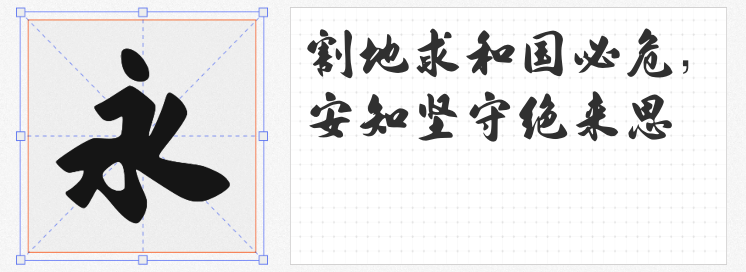
在文创设计的世界里,字体不仅是信息的载体,更是情感与文化的视觉表达。以下四款免费商用字体,以独特的风格与强适配性,为文创作品注入鲜活的个性,助力设计师轻松打造高辨识度作品。
1. 文心喜乐体
这款字体以“随性不拘谨”为设计核心,字形饱满圆润,笔画错落有致,横竖粗细对比强烈,形成视觉节奏感。高光纹理的加入赋予其手作质感,仿佛孩童涂鸦般充满天真趣味。无论是作为标题的吸睛焦点,还是正文的温馨陪伴,都能传递出轻松愉悦的氛围,尤其适合儿童文创、手账周边及生活类品牌设计。
2. 字库江湖古风体
以“古朴韵味”为基调,这款字体通过粗壮有力的笔画与柔和的视觉处理,平衡了历史厚重感与现代亲和力。它既保留了传统书法的骨力,又通过圆角处理减少锐利感,适用于餐饮品牌、传统工艺文创及国潮风格设计。无论是招牌、包装还是文化海报,都能以沉稳而不失温度的气质传递品牌底蕴。
3. 字体家AI造字霸行
由叶根友手写基础结合AI生成的这款字体,以“铿锵有力”的笔触展现力量美学。笔画刚劲挺拔,转折处利落分明,既保留了手写的自然韵律,又通过技术优化提升了排版适用性。适合需要强调品牌态度的文创场景,如潮玩包装、音乐节海报或运动品牌视觉,用硬朗风格传递个性主张。
4. 也字工厂小石头体
这款字体以“柔软可爱”为灵魂,字形如圆润石子般Q弹,笔画自由洒脱,软笔特征的运用让其充满灵动气息。粗细对比强烈的笔画设计,既保留了童趣的视觉冲击力,又通过圆角处理传递温暖感。广泛适用于文创IP形象、儿童读物、手作品牌及社交媒体图文,为作品增添一抹治愈系活力。
这四款免费商用字体,或稚拙、或古朴、或刚劲、或Q弹,以多样化的风格满足文创设计的多元需求。选择它们,即是让设计拥有更自由的表达空间,用笔触的温度唤醒作品的独特生命力。